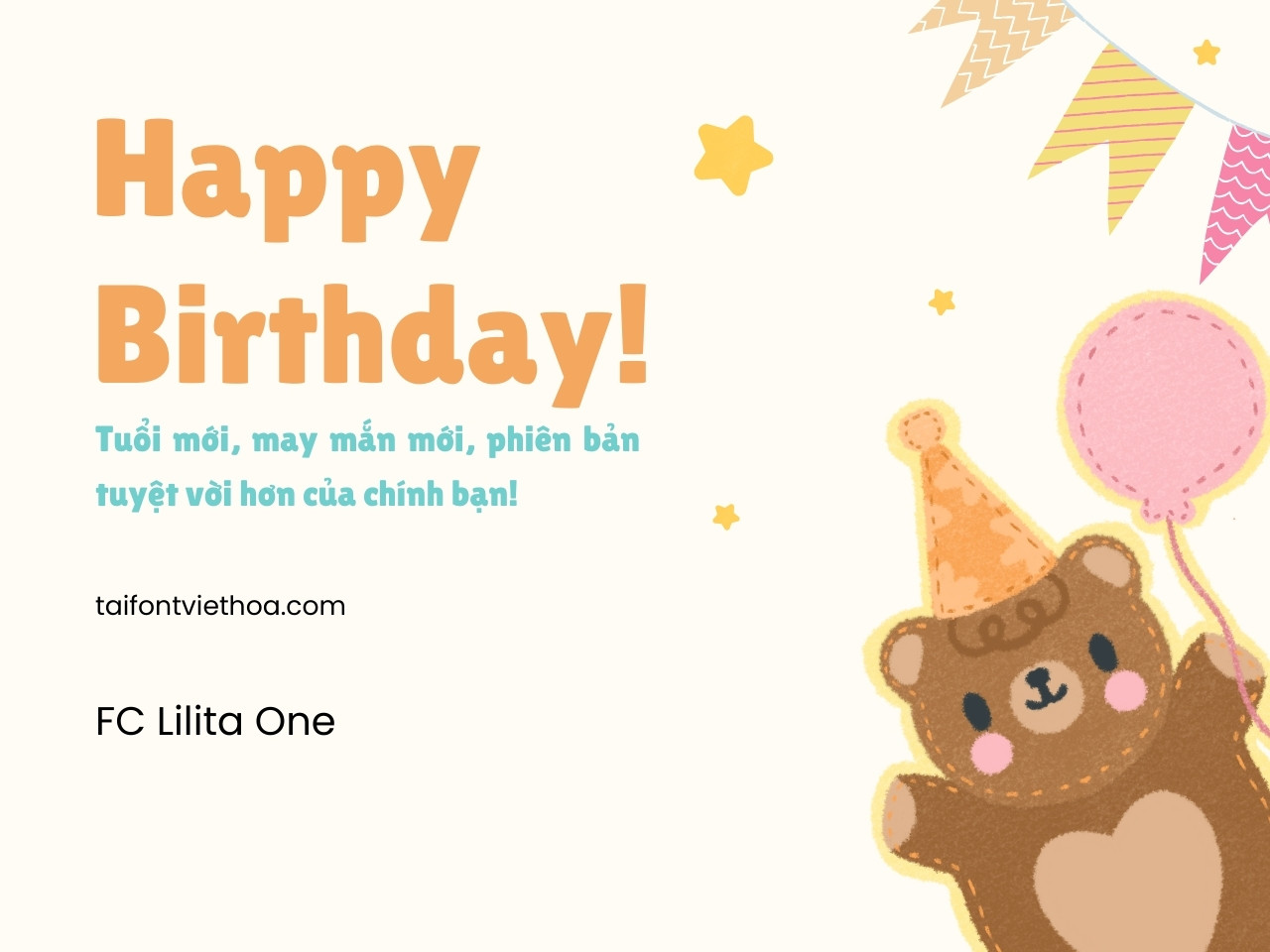
Giới thiệu về font Lilita One và phiên bản Việt hóa
FC Lilita One là phiên bản Việt hóa từ font gốc “Lilita One” – một thiết kế sans-serif mang phong cách hiện đại, tươi vui và dễ tiếp cận, được sáng tạo bởi Juan Montoreano và phát hành chính thức trên Google Fonts. Với các đường nét tròn trịa, kích thước chữ to rõ và khả năng thu hút thị giác mạnh mẽ, Lilita One là lựa chọn lý tưởng cho các tiêu đề, poster, banner số hoặc giao diện người dùng. Font hỗ trợ hơn 150 ngôn ngữ bao gồm bảng Latin, Cyrillic và Greek, được ứng dụng rộng rãi trên toàn cầu.
Đây là phiên bản Việt hóa hoàn toàn độc lập, khác biệt với bản “1FTV VIP Lilita One” đã được phát hành trước đó. FC Lilita One được thực hiện bởi cộng đồng Font Chuẩn, với hệ thống dấu tiếng Việt được thiết kế lại tỉ mỉ nhằm đảm bảo độ cân đối, mượt mà và tương thích tốt với mọi trình gõ Unicode. Font vẫn giữ trọn tinh thần mềm mại – trực quan – dễ đọc của bản gốc, nhưng được tối ưu để sử dụng trong môi trường thiết kế tiếng Việt.
Đặc điểm thiết kế và ứng dụng thực tế
FC Lilita One có thiết kế đặc trưng bởi các đường cong mềm mại, độ đậm đồng đều và cấu trúc chữ lớn giúp tăng cường khả năng đọc ở kích thước nhỏ. Các chữ cái có chiều ngang rộng, phần đầu chữ tròn và không chân, tạo nên tổng thể vui nhộn, thân thiện nhưng vẫn giữ sự chuyên nghiệp. Kiểu chữ này không chỉ hiệu quả trong thiết kế tiêu đề mà còn dùng tốt trong các mẫu banner, slide thuyết trình, và ứng dụng giáo dục dành cho trẻ em.
FC Lilita One rất phù hợp với các ngành như giáo dục, truyền thông, sản phẩm cho trẻ em, ẩm thực sáng tạo, bảng hiệu quảng cáo, thiết kế UI/UX và các chiến dịch marketing cần yếu tố vui tươi, dễ tiếp cận. Đây là một lựa chọn đáng tin cậy cho những ai muốn tạo ấn tượng nhanh chóng qua font chữ.